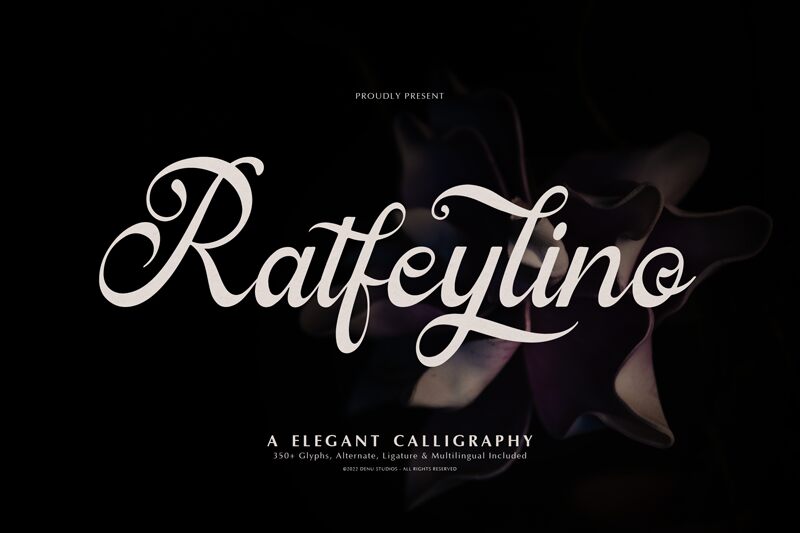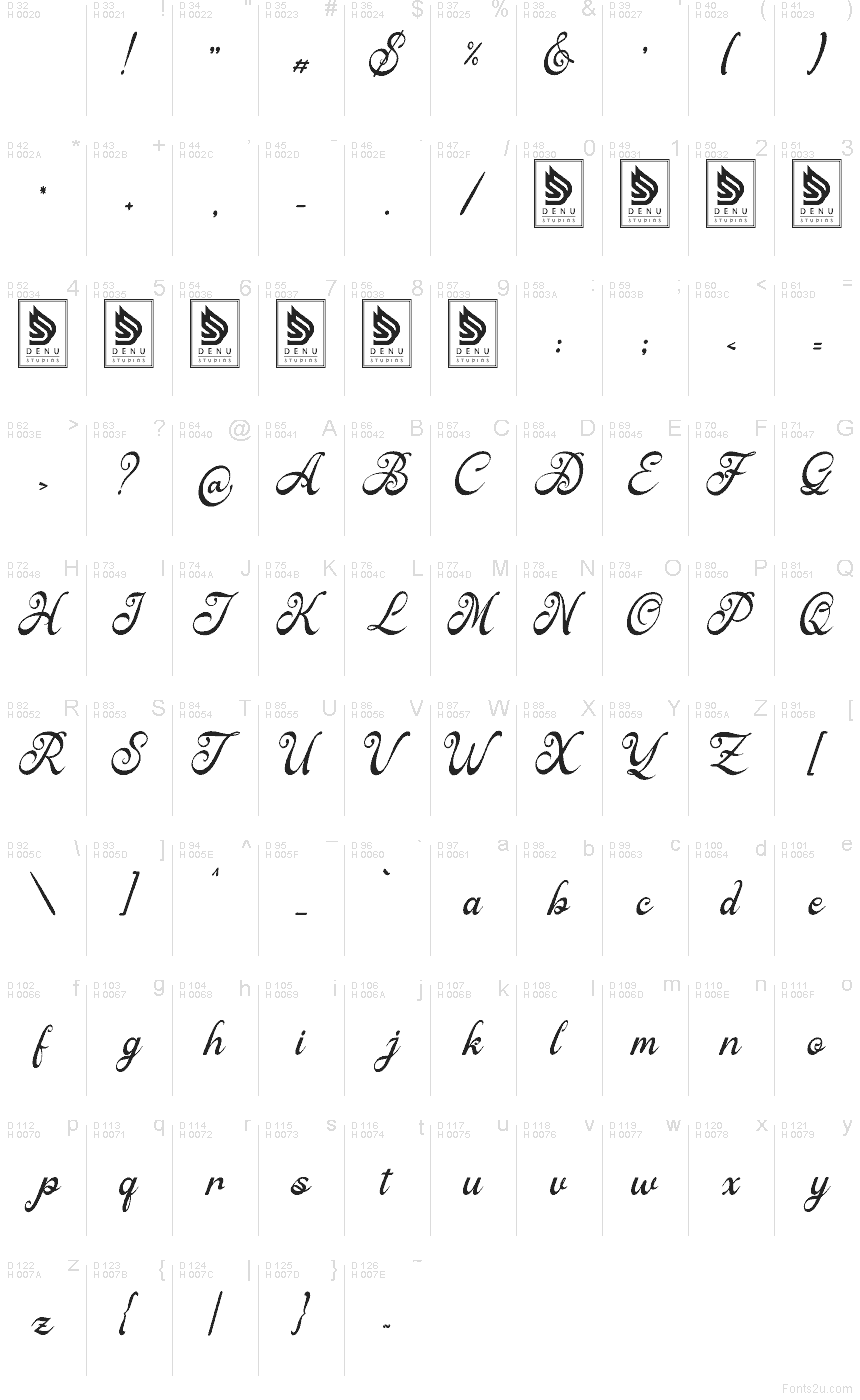
Ratfeylino es una tipografía caligráfica gratuita de Denustudios, con un estilo script formal definido por trazos de entrada amplios y bucles ligeros. Sus letras evocan la elegancia de una invitación de boda, mezclando curvas fluidas con algunos giros más definidos para que el resultado sea elegante pero natural, nunca rígido.
Esta fuente gratuita se adapta perfectamente al branding de boutiques, packaging de belleza, tarjetas de felicitación, portadas de libros y titulares de carteles que necesiten un toque romántico. También funciona de maravilla en títulos, logotipos y monogramas, ya que sus largos trazos y descendentes rizadas aportan movimiento propio a las palabras cortas.